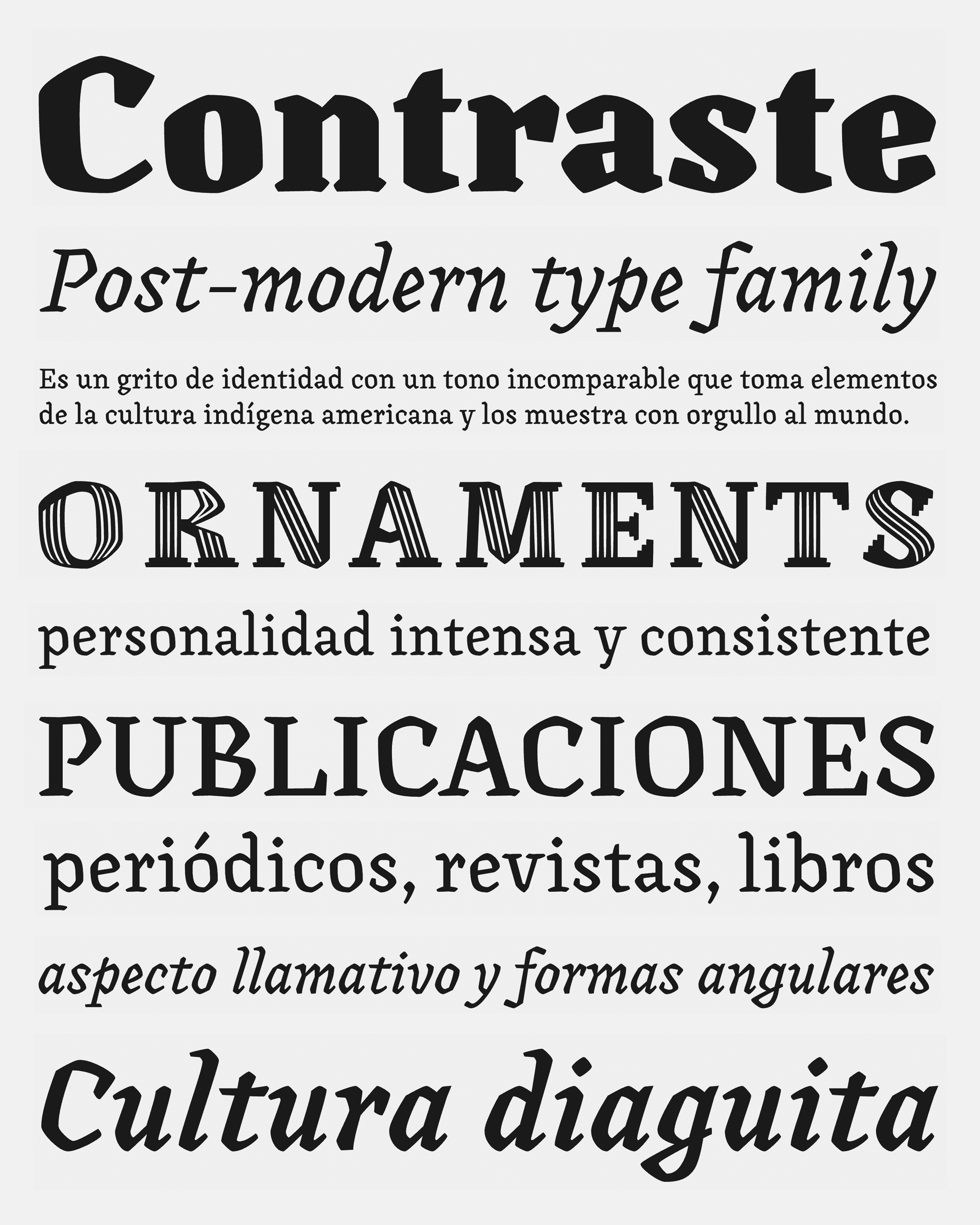
| Descripción | Canilari es una familia tipográfica posmoderna inspirada en la cerámica diaguita y en las tipografías con serif contemporáneas. La cultura Diaguita —desarrollada desde el siglo X d.C. hasta el siglo XVI d.C.— se asentó en la zona del actual norte de Chile y noroeste de Argentina. Las expresiones culturales que han sobrevivido de este pueblo se reducen a unas pocas piezas de cerámica bellamente decorada y de gran calidad técnica. |
| Familia(s) | Canilari Ornaments, Canilari Regular, Canilari Regular Italic, Canilari Medium, Canilari Medium Italic, Canilari Bold, Canilari Bold Italic, Canilari Heavy, Canilari Heavy Italic |